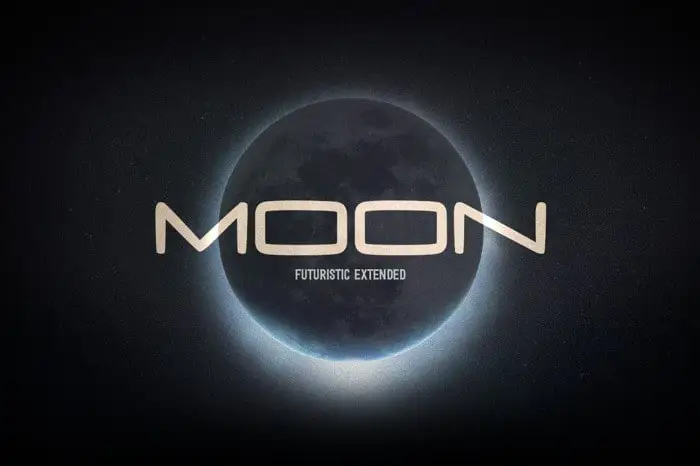
A Moon Display Font é uma seleção única para aqueles que buscam criar designs futuristas e sci-fi. Ela foi criada por DonMarciano especialmente para mensagens curtas, talvez usadas em um log padrão na superfície de uma estação espacial durante uma aventura longe da Terra. O propósito é aproveitar os formatos ampliados da fonte que transmitem perfeitamente o ritmo rápido e a sensação futurista e de ficção científica. Acredita-se que seja perfeito para projetos com um tema estranho vindos do espaço. Através da influência dos traços originais feitos à mão, esta fonte apresenta linhas limpas e desiguais, oferecendo uma aparência vibrante que reflete o espírito de um futuro promissor e a cultura do espaço. Com seu design único e versátil, Moon Display Font é uma ótima escolha para aqueles buscando imprimir sua marca com o impacto imediato e inconfundível associado às histórias de viagem no espaço.